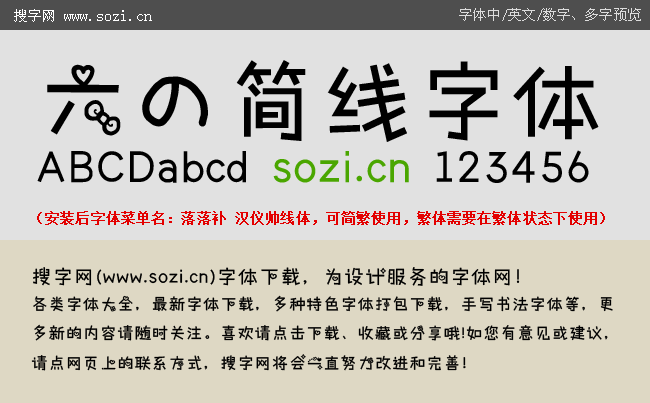
六の简线字体
搜字网给大家提供一款俏皮可爱的手机中文字体下载。修改者叫它六の简线字体,这款手机字体是在汉仪帅线体笔画间插入了卡通图案。汉仪帅线体运用平头和直线描绘,笔画设计上硬朗,部件设计上有棱角、直接。力求现男孩子直率的性格。字与字之间依据字本身结构特质有大小变化,营造跳跃和俏皮之感。使整体形象不呆板。加入了卡通图案后又增添了趣味性,特别适合喜欢手机字体个性一些的朋友在手机上安装使用。